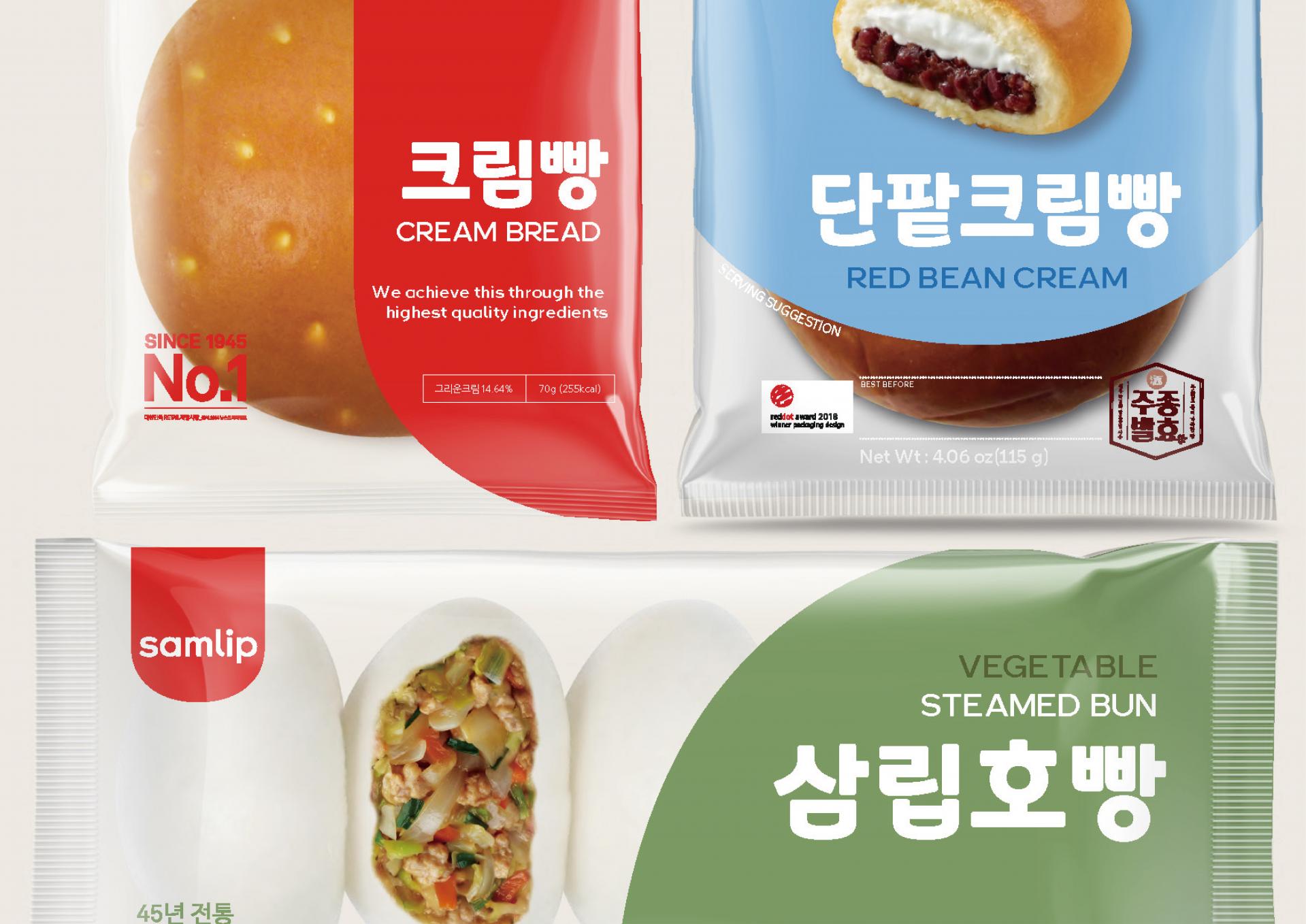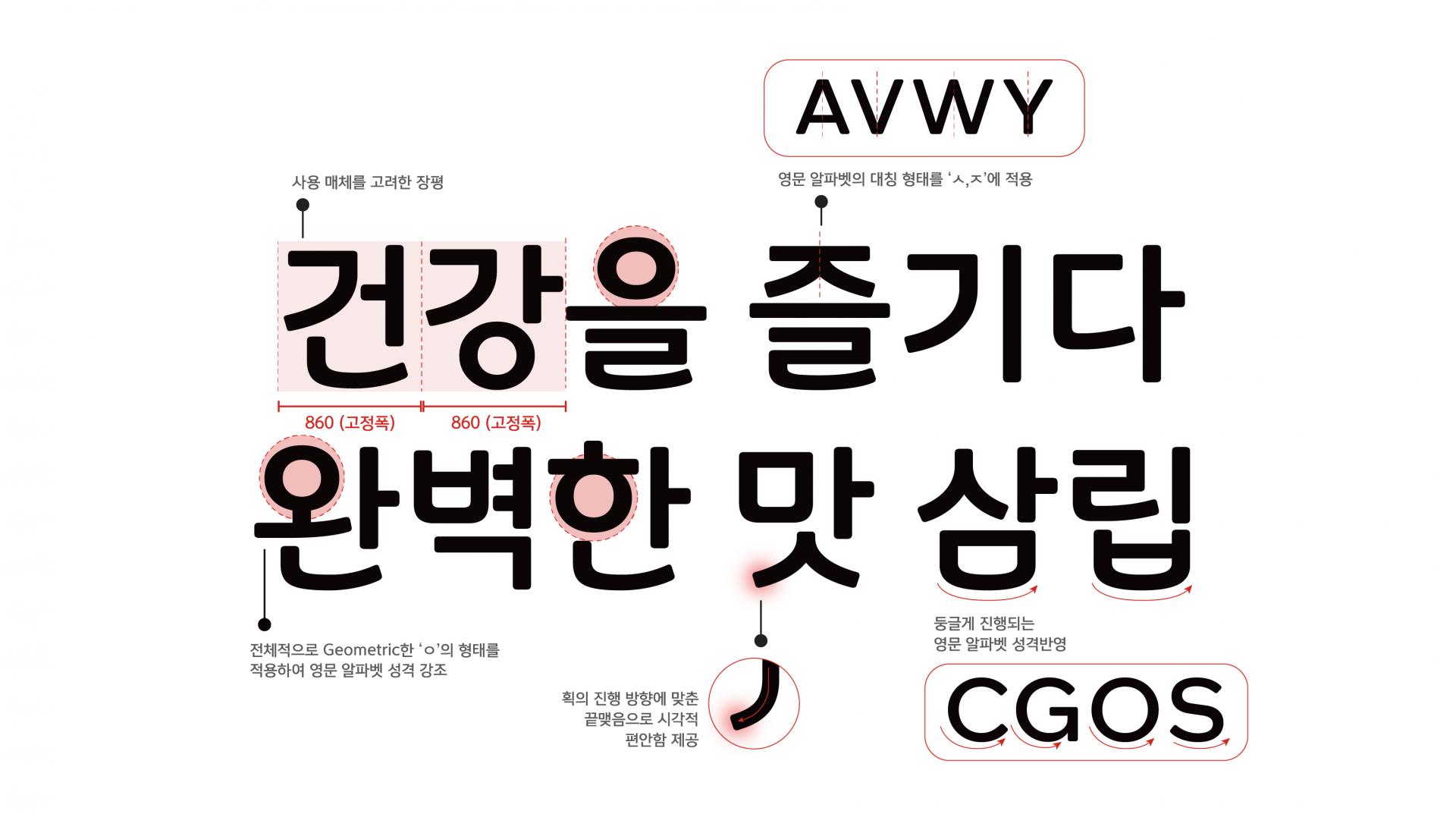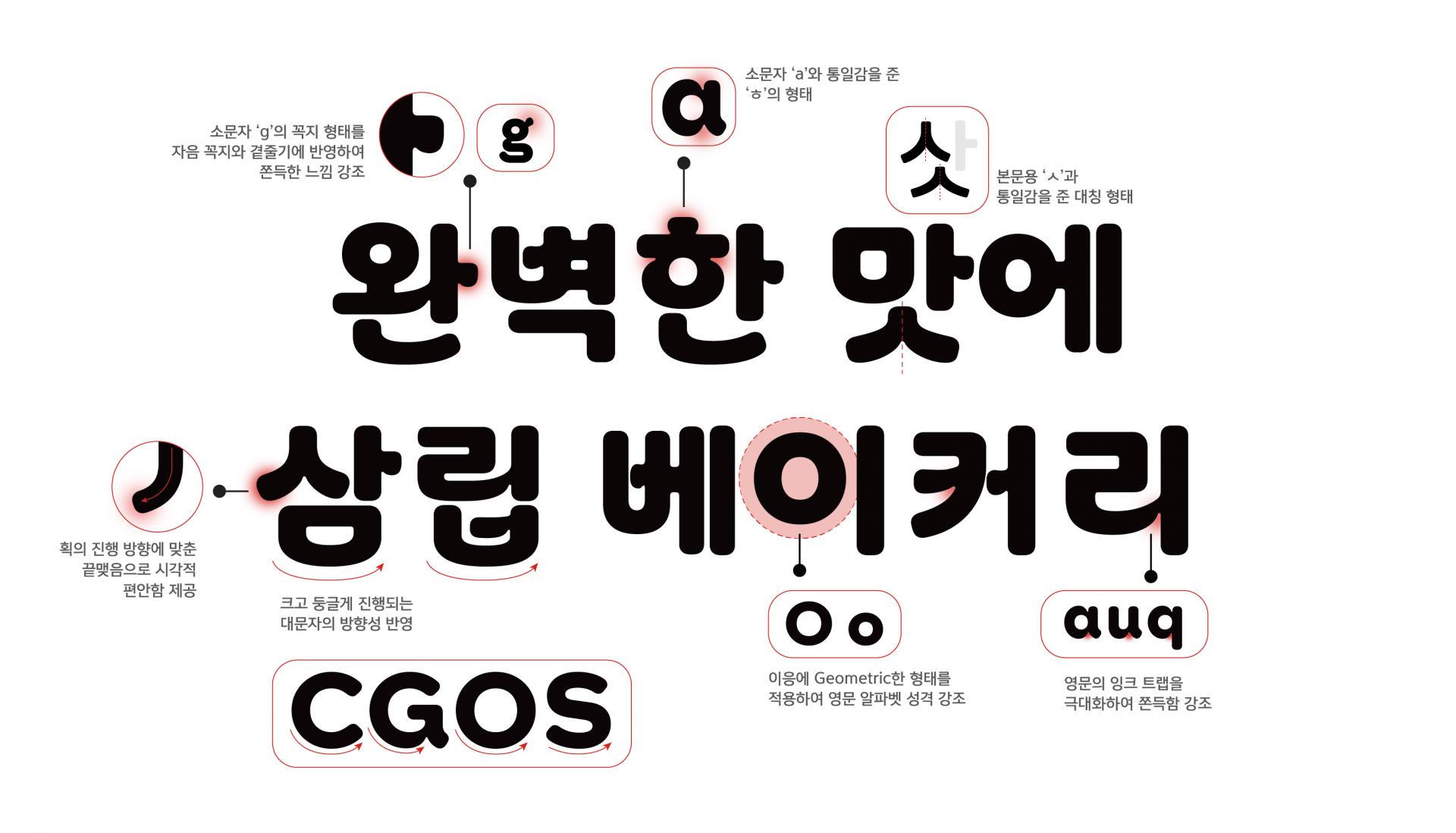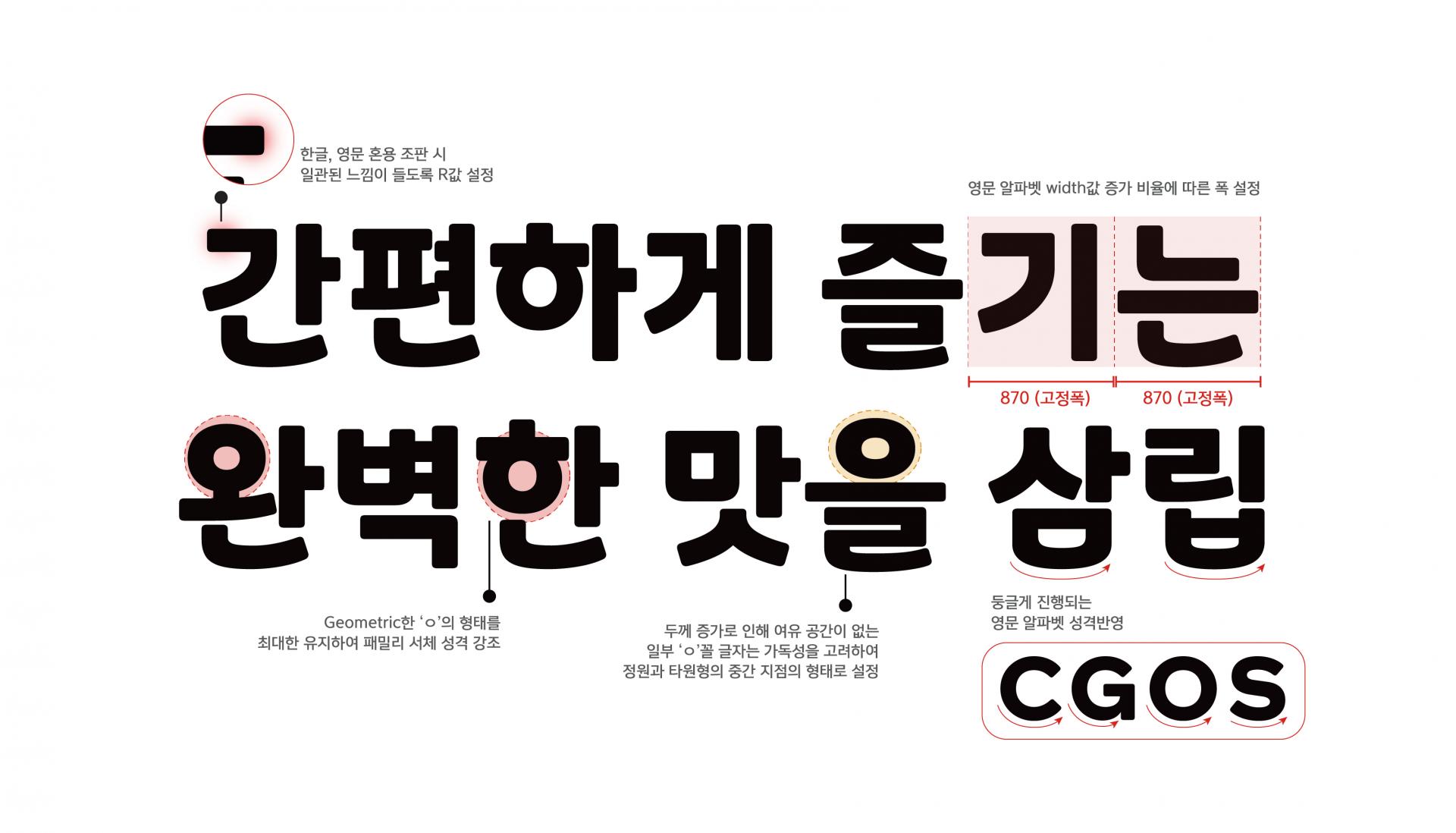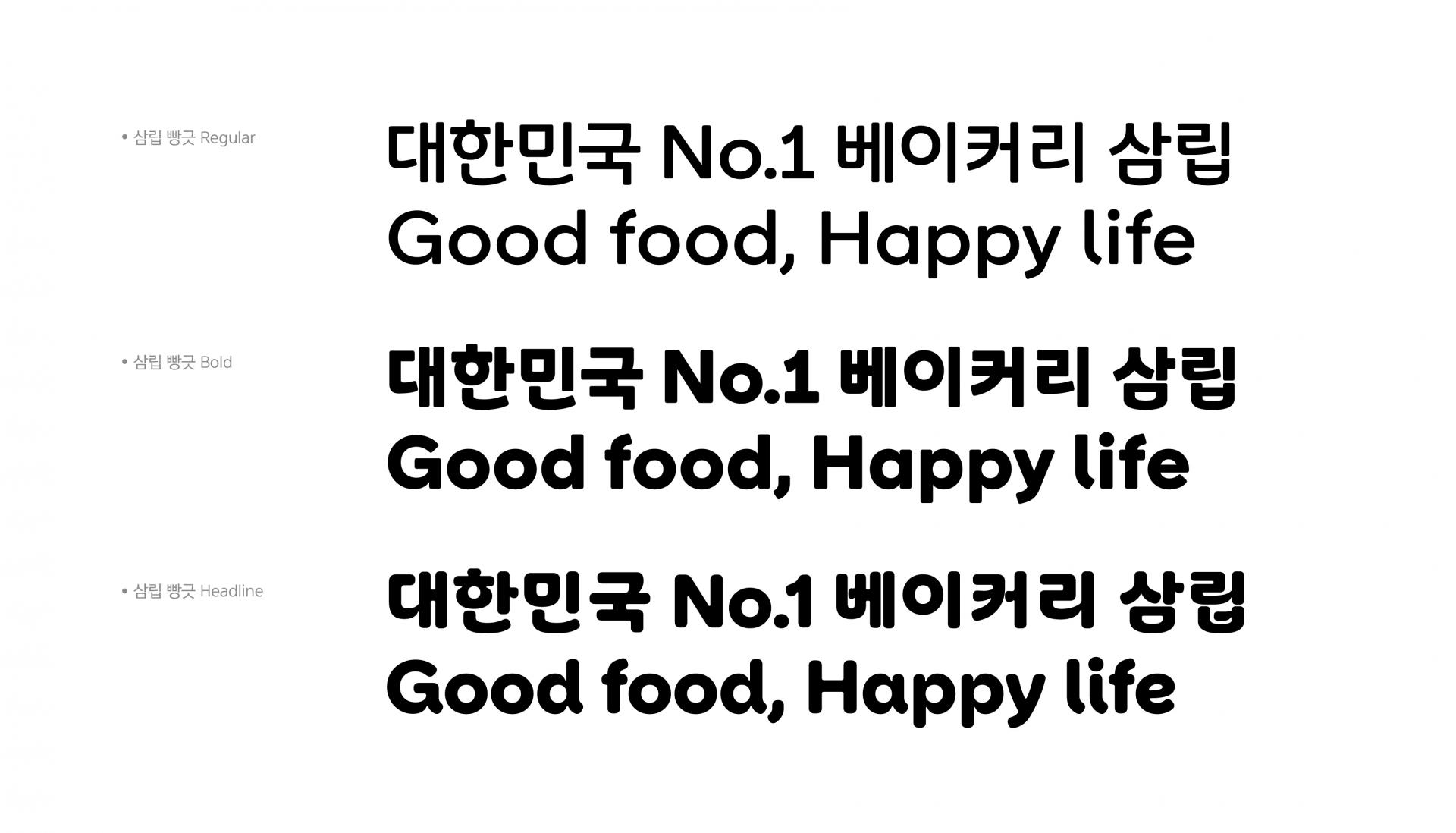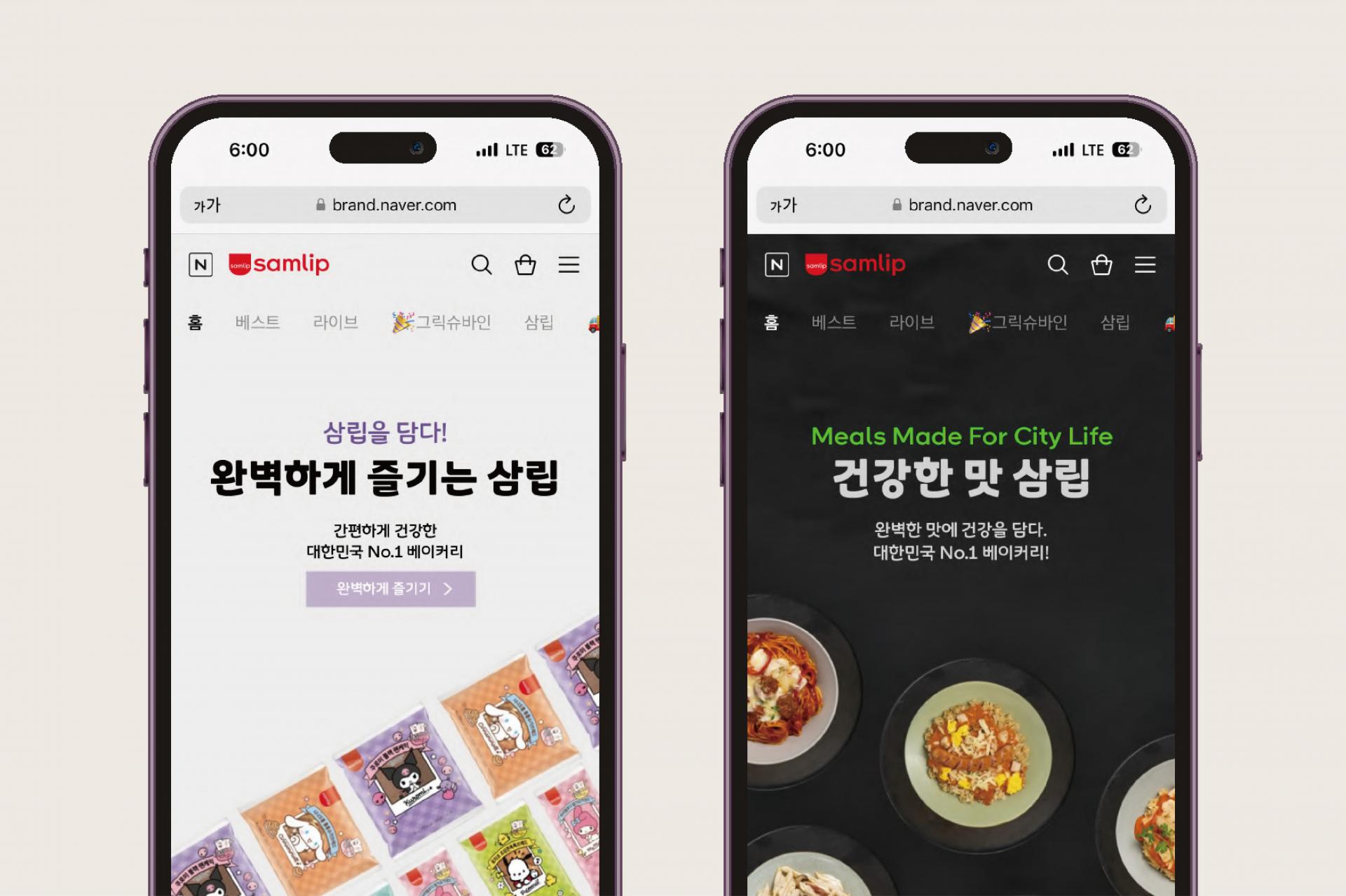
SPC 삼립 [삼립빵긋체]
같은 재료를 사용하여도 최적의 발효 온도와 시간에 따라 완벽한 풍미와 식감을 가진 맛있는 빵이 나오듯, '삼립 빵긋체 Regular/Bold'는 '상미당 정신'이 재료가 되어 삼립만의 스토리를 담고 쓰임새를 최우선으로 고려하여 최적의 서체로 제작하였다. 이러한 과정으로 제작된 '삼립 빵긋체'는 삼립의 색이 담겨있는 서체로, 삼립만의 이미지를 다채롭게 나타내었다.